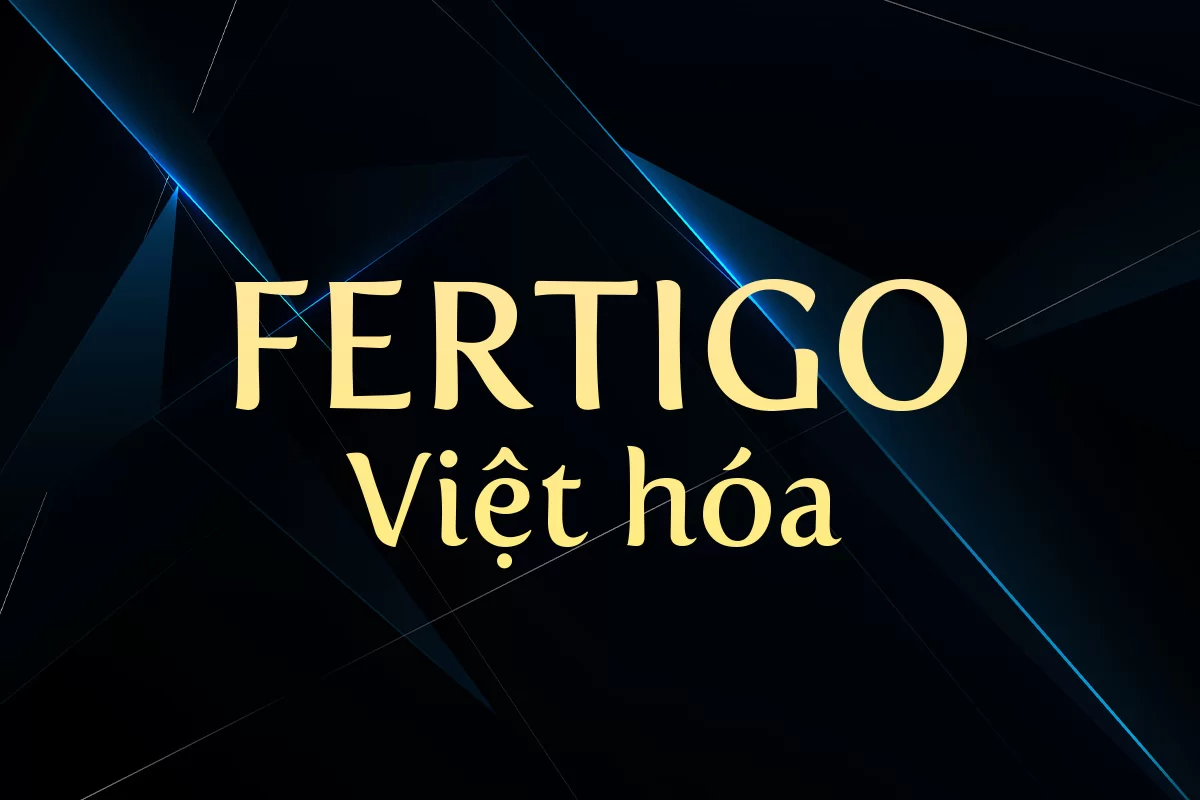
Fertigo Việt hóa là một serif font đầy cá tính với những đường cong bất đối xứng nhẹ, tạo nên vẻ đẹp thanh lịch pha chút nổi loạn. Các chữ cái được thiết kế không theo chuẩn khuôn mẫu nghiêm ngặt, mang đến cảm giác tự do, phóng khoáng nhưng vẫn giữ được sự tinh tế và dễ đọc. Font đặc biệt phù hợp cho các thiết kế mang tính sáng tạo cao như bìa sách, tiêu đề nghệ thuật, poster trừu tượng hoặc dự án cá nhân độc đáo. Bản Việt hóa được tối ưu đầy đủ dấu tiếng Việt, đảm bảo tính ứng dụng cao mà vẫn giữ nguyên phong cách lạ mắt vốn có của Fertigo.